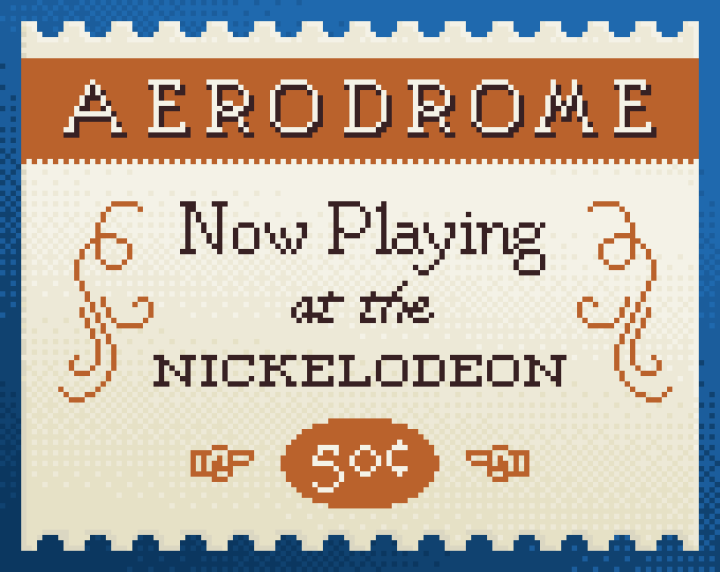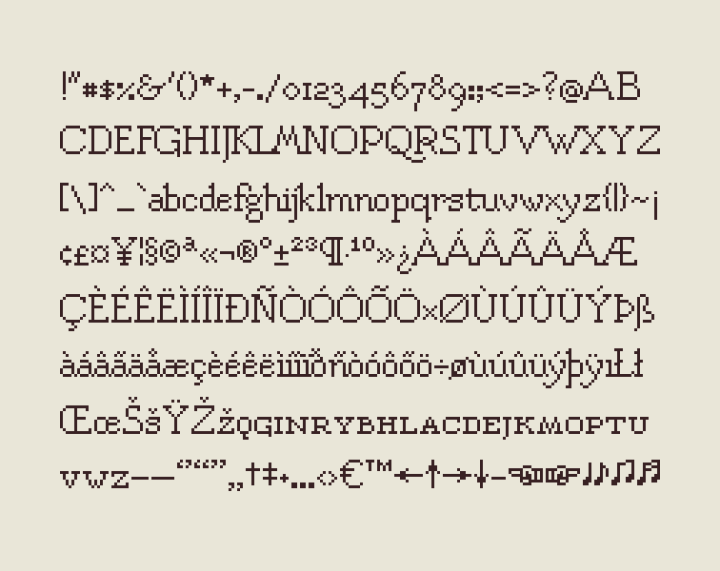
一种1910年代风格的Aerodrome像素字体素材,可满足您所有的像素艺术需求。它的 x 高度为 6 像素,总高度为 14 像素。Aerodrome 包含小型大写字母和许多带重音符号的字符。 您可以将此字体用于您自己的商业或非商业作品中。 声明:本站所有文章,均来源于网络用户收集上传。如若本站内容侵犯了原著者的合法权益,可联系我们进行处理。